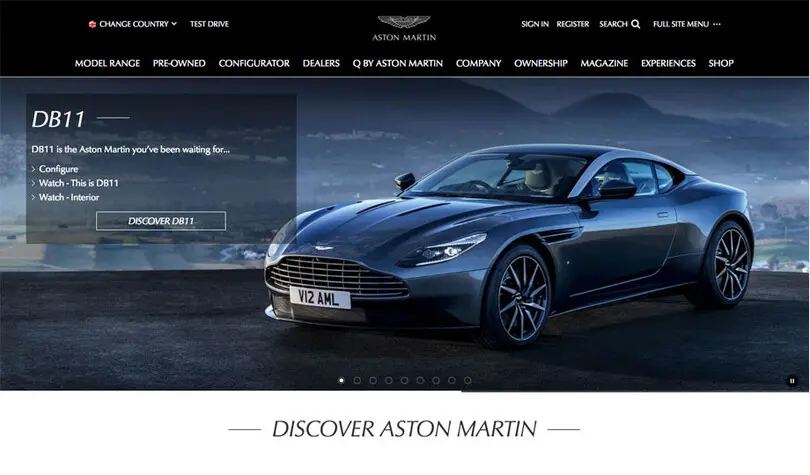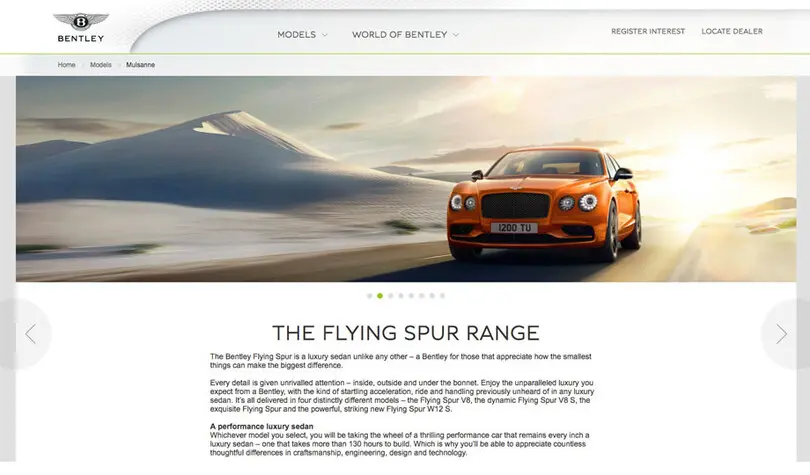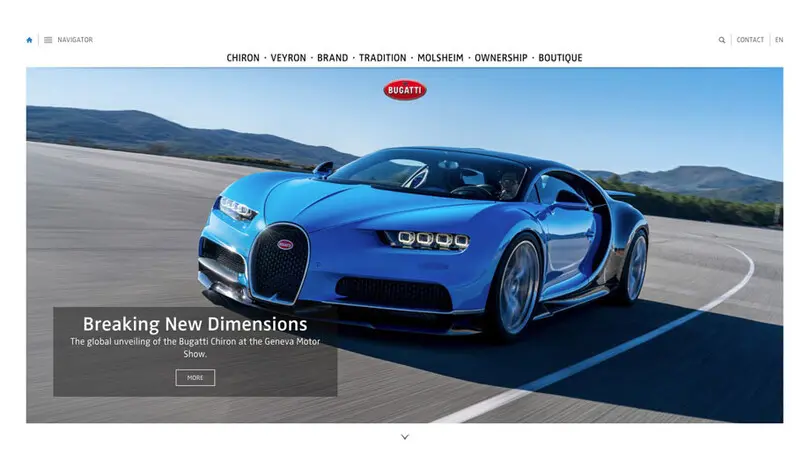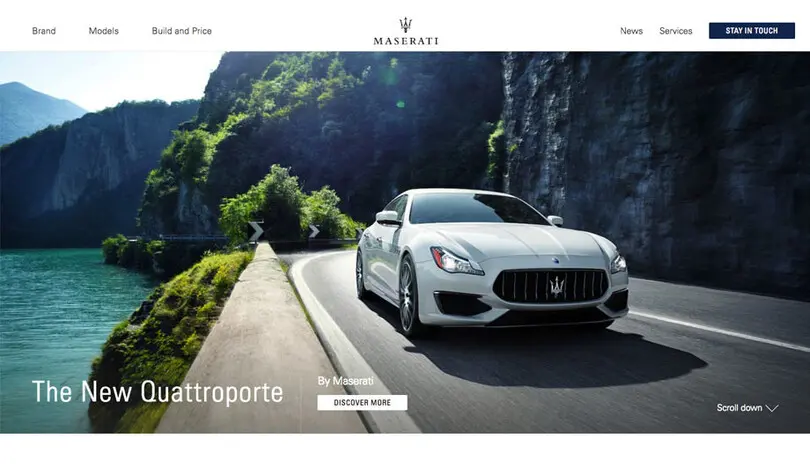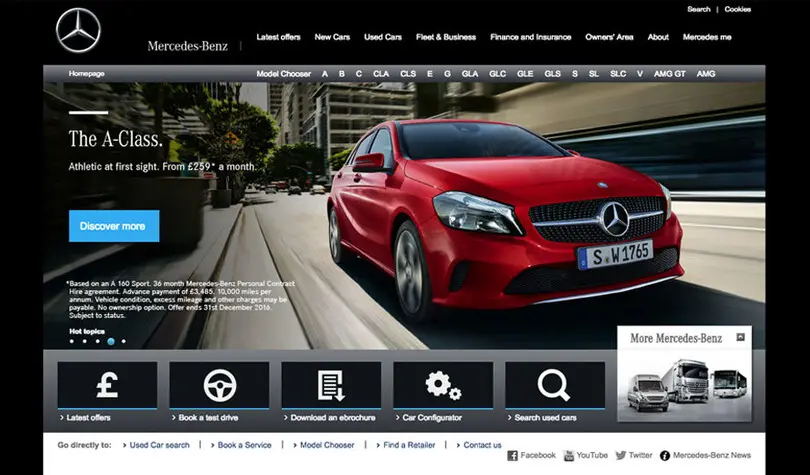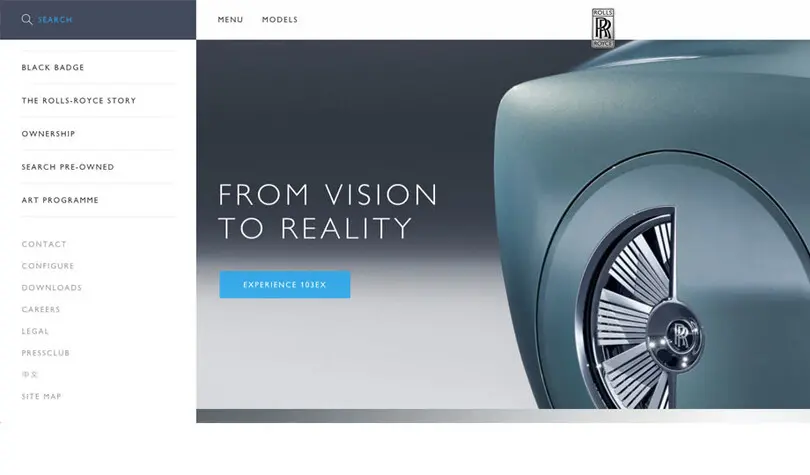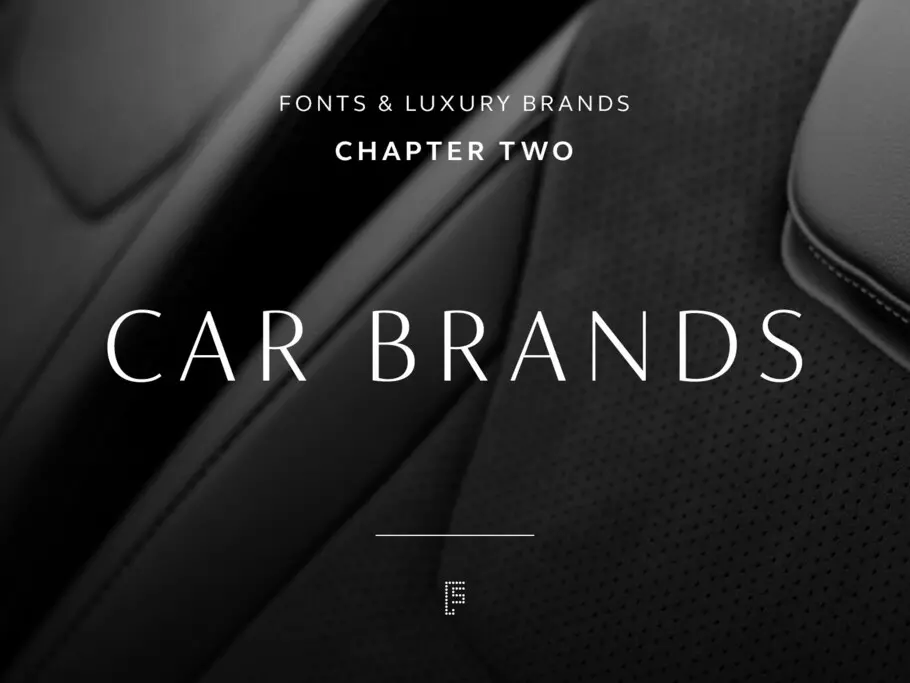
Polices et marques de luxe : l'automobile.
Dans la deuxième partie de notre étude sur le secteur du luxe et l’utilisation des styles typographiques, nous nous intéressons au secteur automobile.
Encore considérée comme une industrie largement dominée par les hommes, nous avons voulu voir s’il existait des similitudes avec notre précédente étude sur le secteur de la beauté. Comment les marques automobiles utilisent-elles les polices pour exprimer à la fois le luxe, la puissance, la vitesse et la précision ?
Maserati
Maserati met en avant son prestigieux héritage sportif, forgé par des décennies d’excellence. La police à empattement classique Bembo, utilisée dans son logo, apporte un sentiment de tradition. Cependant, l’association avec Univers 45 (standard) et Univers 47 (condensé) donne un ton froid et impersonnel. Ces choix typographiques ne traduisent pas la dimension artisanale et exclusive que Maserati cherche à atteindre, offrant au contraire une sensation mécanique et standardisée.
Mercedes
Corporate A est une police moderne à fort contraste avec des empattements raffinés. Elle est utilisée sur l’ensemble des supports de la marque allemande — impression, web et signalétique — aux côtés de Corporate S, sa version sans serif. Ces polices sont parfaitement proportionnées, classiques, élégantes et sophistiquées. Arial est utilisée en complément pour la navigation et les textes courants. Parmi les dix marques étudiées ici, Mercedes est la seule à ne pas recourir systématiquement aux majuscules.
Ferrari
Ferrari mêle plusieurs styles typographiques, allant de Compatil Letter (une police avec empattement proche de son logo) à la sans serif géométrique Proxima Nova pour les textes courants. En changeant de rubrique, le texte de corps bascule de Proxima Nova à Lato, une sans serif humaniste aux coins arrondis. On retrouve également Times New Roman dans de nombreuses sections, notamment pour les légendes. Ce manque de cohérence nuit à la hiérarchie visuelle de la marque. Ferrari est, avec Mercedes, l’une des deux seules marques parmi les dix étudiées à afficher son logo en minuscules.
Jaguar
La police principale de Jaguar est une sans serif modulaire et étendue, reprenant les proportions du logo Jaguar, mais avec moins de contraste. Cette police sur mesure, créée par Fontsmith, se distingue par des lignes nettes et des courbes audacieuses et puissantes. Le logo, la navigation et les titres sont tous en majuscules, tandis que Proxima Nova est utilisée pour les titres, la navigation et les textes de corps. Un équilibre parfait entre une typographie affirmée, des lettres imposantes et une photographie dynamique. Une qualité premium omniprésente.
Aston Martin
Voiture britannique emblématique, souvent associée à James Bond et à une ingénierie de pointe, Aston Martin utilise URW Classico, une variante de la police Optima – une sans serif avec une légère finition au bout des hampes, créant un effet global similaire à une police avec empattement en termes d’élégance et d’héritage. L’utilisation d’une seule famille typographique fonctionne bien ici, apportant une unité et une cohésion visuelle. La typographie d’Aston Martin rappelle celle de nombreuses marques du secteur de la beauté, avec une omniprésence des majuscules dans le logo, les titres et la navigation.
Porsche
Le logo et la police principale sont issus d’un design modulaire exclusif nommé Porsche Sans, également utilisé pour les noms des modèles et les légendes. Sur le site web, Franklin Gothic est employée pour les titres, créant un impact fort et percutant (accompagné de News Gothic pour les sous-titres). Étonnamment, Arial est utilisée pour la navigation et les textes courants, en contradiction avec l’image haut de gamme de la marque.
Pagani
Petite entreprise ne produisant qu’un nombre limité de supercars chaque année, Pagani revendique un savoir-faire artisanal exceptionnel. Cependant, la marque utilise la police géométrique Josefin Sans pour les légendes et PT Sans, une sans serif humaniste, pour les textes de corps. Ces polices échouent à refléter l’image d’un artisanat raffiné et fait main, offrant plutôt une allure industrielle et mécanique.
Bugatti
Bugatti utilise une police humaniste étroite nommée Ff-zwo, caractérisée par une grande hauteur d’x, des courbes carrées et des terminaisons ouvertes. Les images sont accompagnées d’une typographie manuscrite au rendu crayonné, renforçant l’aspect artisanal et personnalisé de la marque. L’utilisation de Garamond dans certaines sections apporte une touche d’héritage et d’élégance.
Bentley
Bentley incarne le luxe fait main et un design inimitable. La marque utilise Bentley Sans, une police sur mesure conçue par l’équipe KMS, basée sur une version élargie de Gill Sans, principalement en majuscules. Cette police sans serif géométrique, mais avec des touches humanistes, reflète un héritage britannique avec une esthétique moderne et percutante. L’utilisation systématique des majuscules renforce l’aspect élégant, puissant et affirmé de la marque. Bentley fait également partie des marques utilisant Arial pour les textes courants.
Le secteur automobile semble mieux comprendre l’importance de la typographie que celui de la beauté. La diversité des styles typographiques permet aux marques de se distinguer bien plus que dans l’industrie cosmétique, où les identités visuelles sont souvent similaires. Chaque marque automobile s’appuie sur un riche héritage et privilégie des polices affirmées et robustes, souvent complétées par des créations sur mesure évoquant le savoir-faire artisanal.
L’image d’en-tête est composée en FS Siena, notre nouvelle sans serif contrastée spécialement conçue pour les marques de luxe.